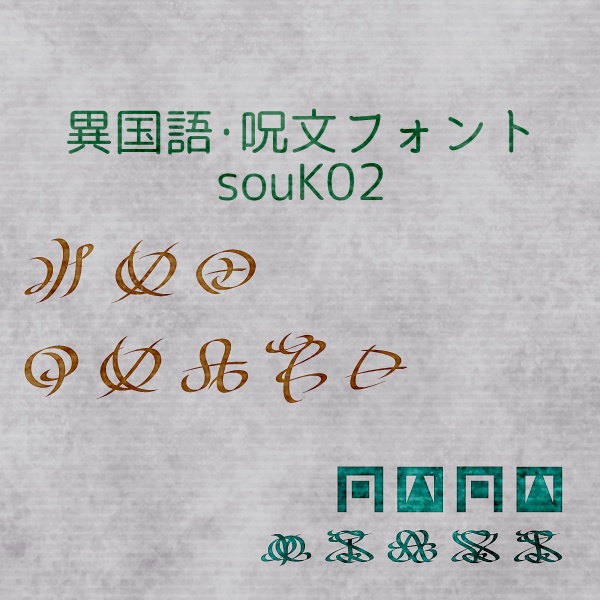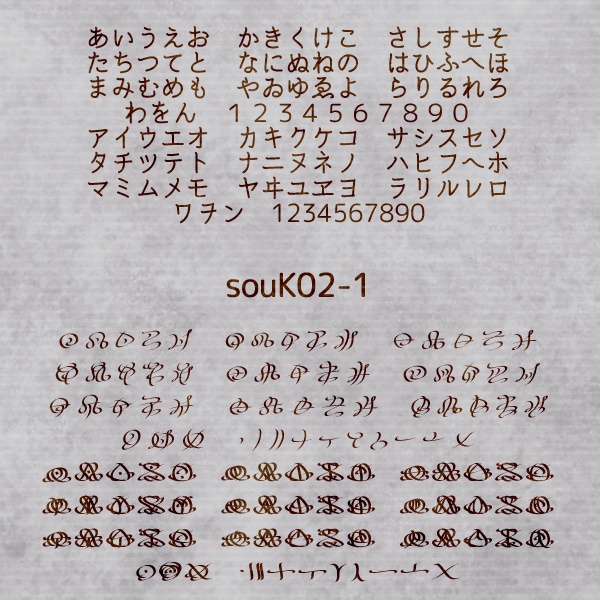
異国語・呪文フォント「souK02」
CLIP STUDIO ASSETSで配布している 「文字ブラシ5」(https://assets.clip-studio.com/ja-jp/detail?id=1754491)を フォント化したものです。 ヲシテ文字をベースにアレンジした、未知の言語っぽい文字列を 作成するためのフォント(OpenTypeフォント)です。 書体は曲線タイプ(02-1)と直線タイプ(02-2)の2種です。 【注意事項】 著作権は放棄しておりません。 意匠・商標登録などに使用することはご遠慮ください。 フォントデータの販売・再配布もご遠慮ください。 その他の使用についてはご自由に。 また、当フォントの使用により損害などが生じても、 一切の責任を負いませんのでご了承ください。 【タイプ可能な文字】 ・02-1、02-2共通 あいうえお かきくけこ さしすせそ たちつてと なにぬねの はひふへほ まみむめも やゆよ らりるれろ わをん 0123456789 ・02-1のみ アイウエオ カキクケコ サシスセソ タチツテト ナニヌネノ ハヒフヘホ マミムメモ ヤユヨ ラリルレロ ワヲン 0123456789